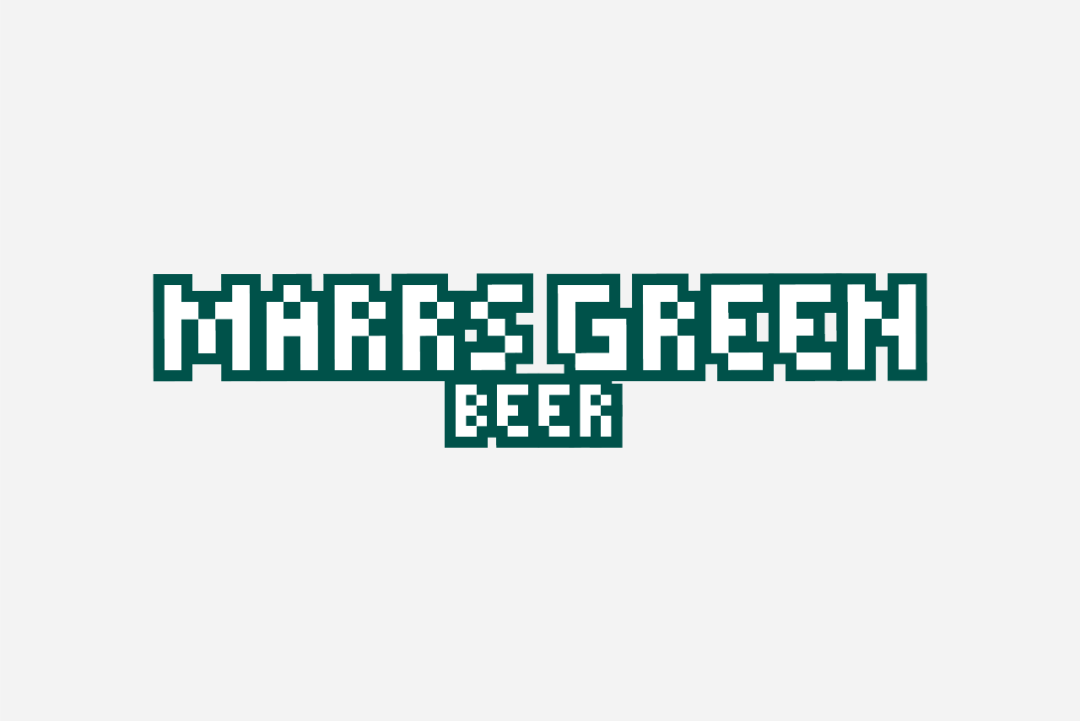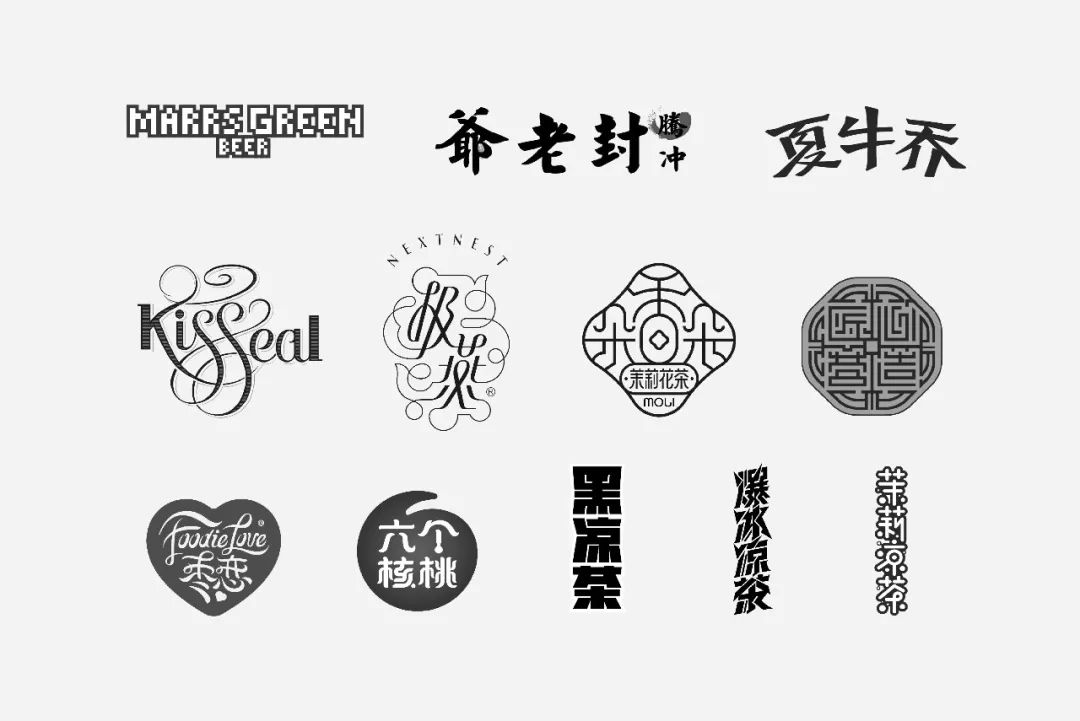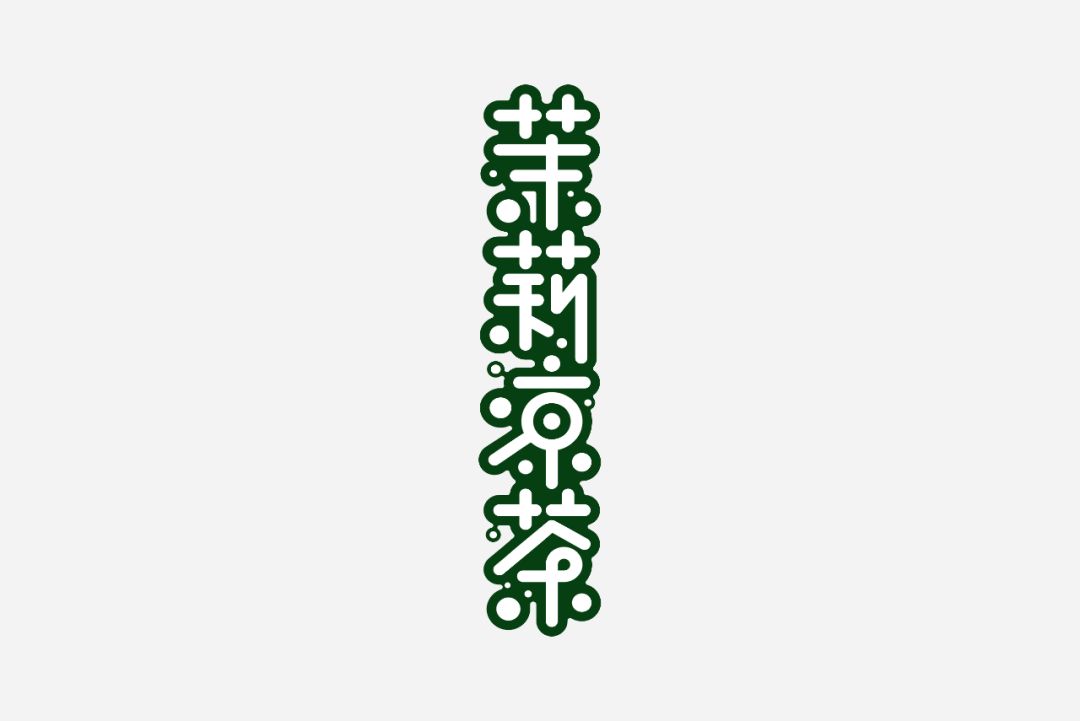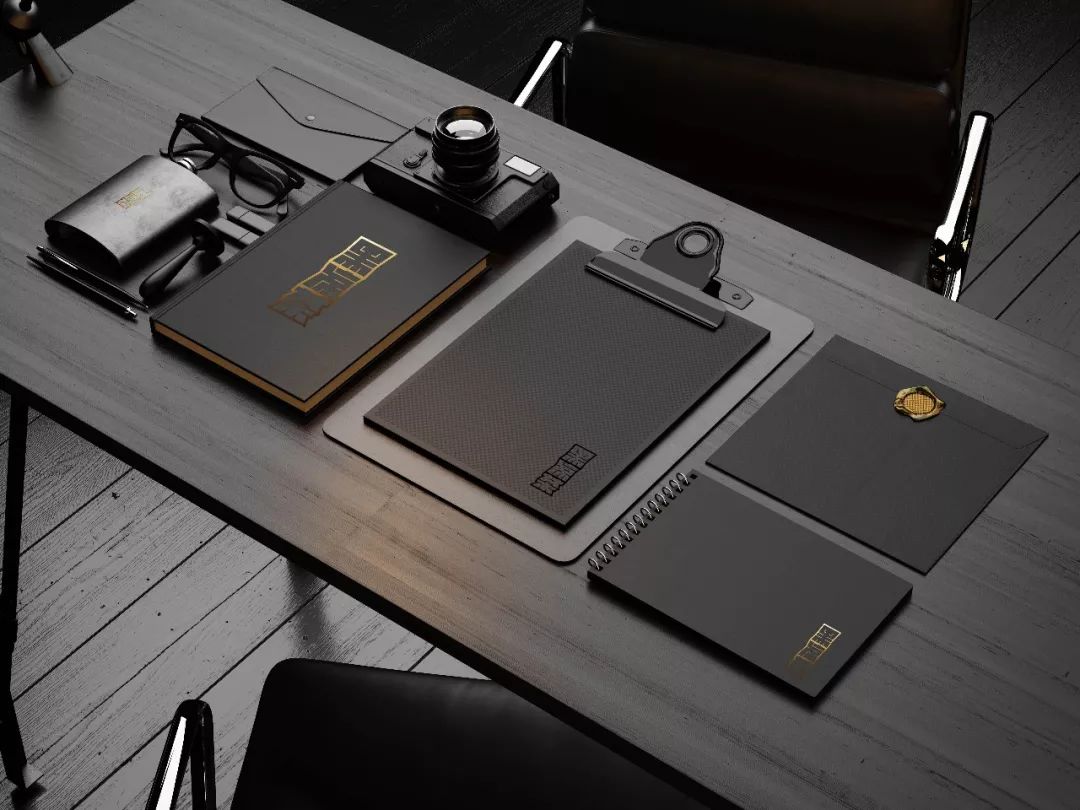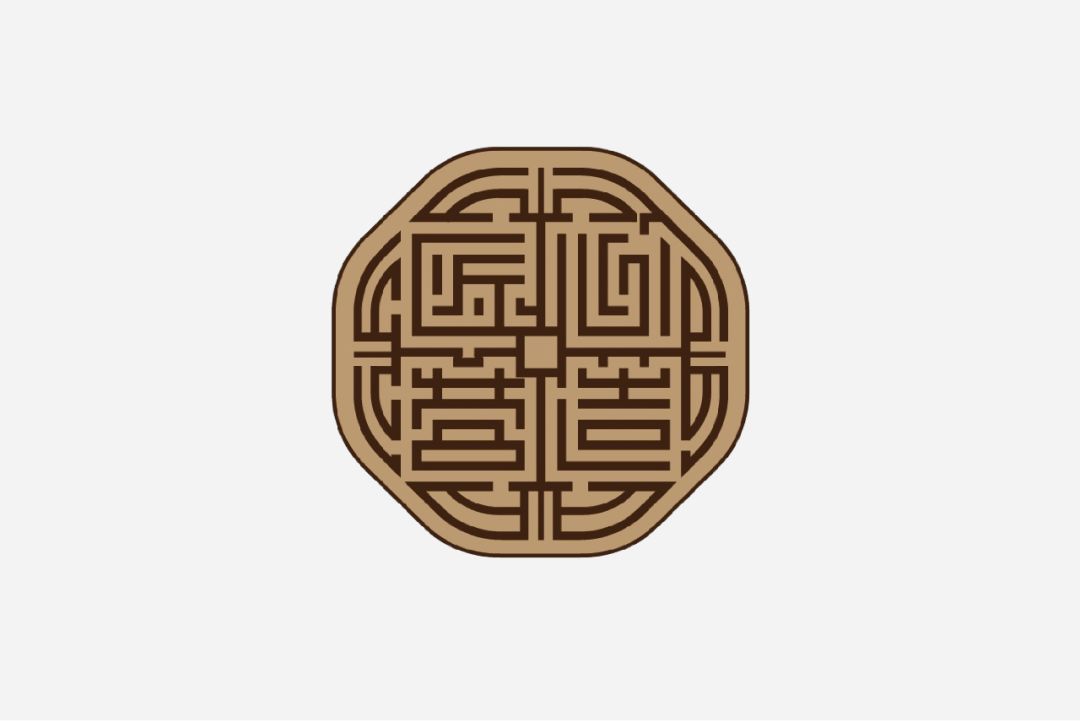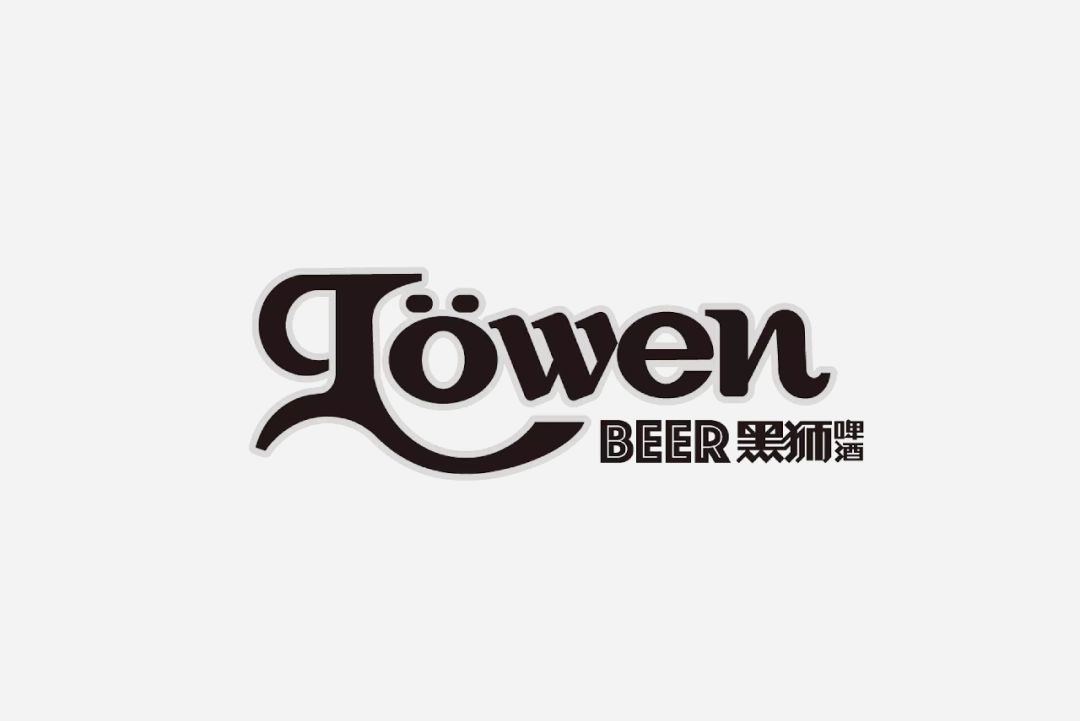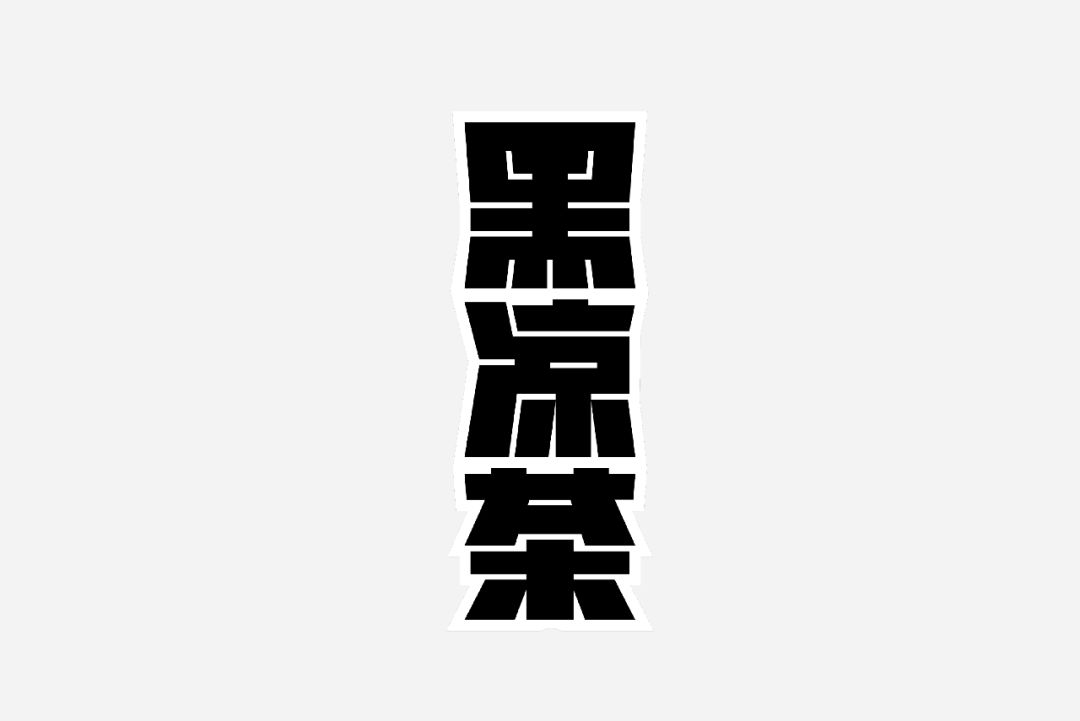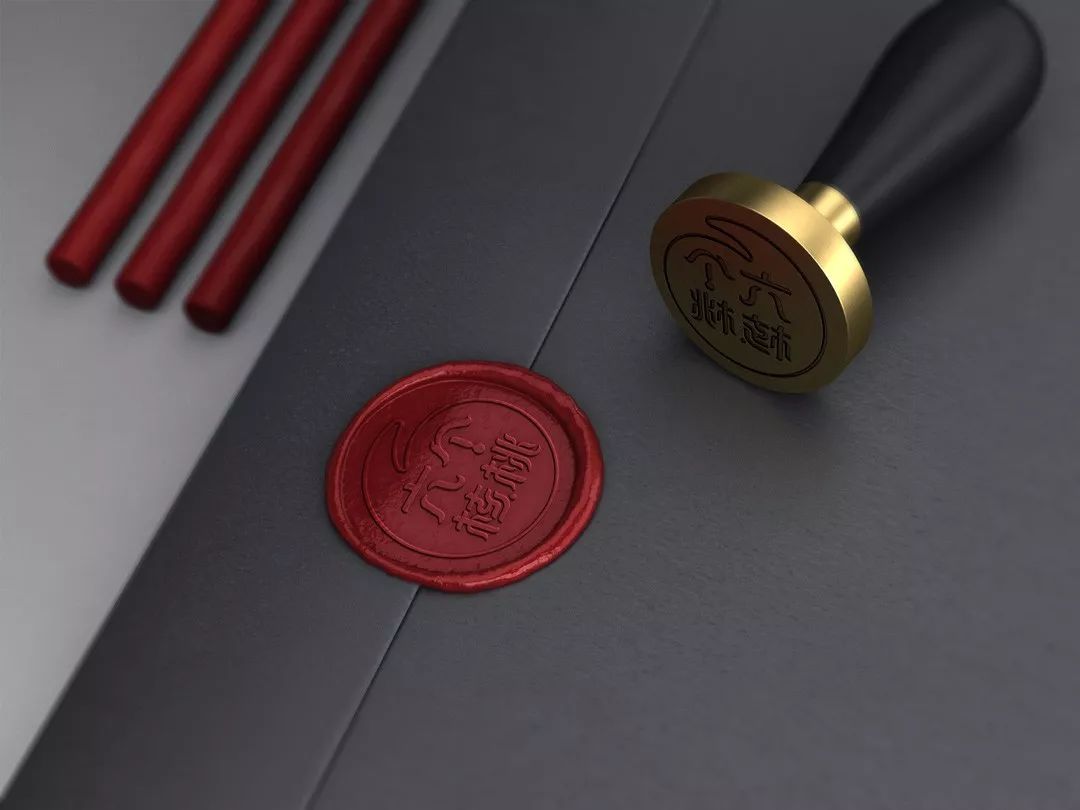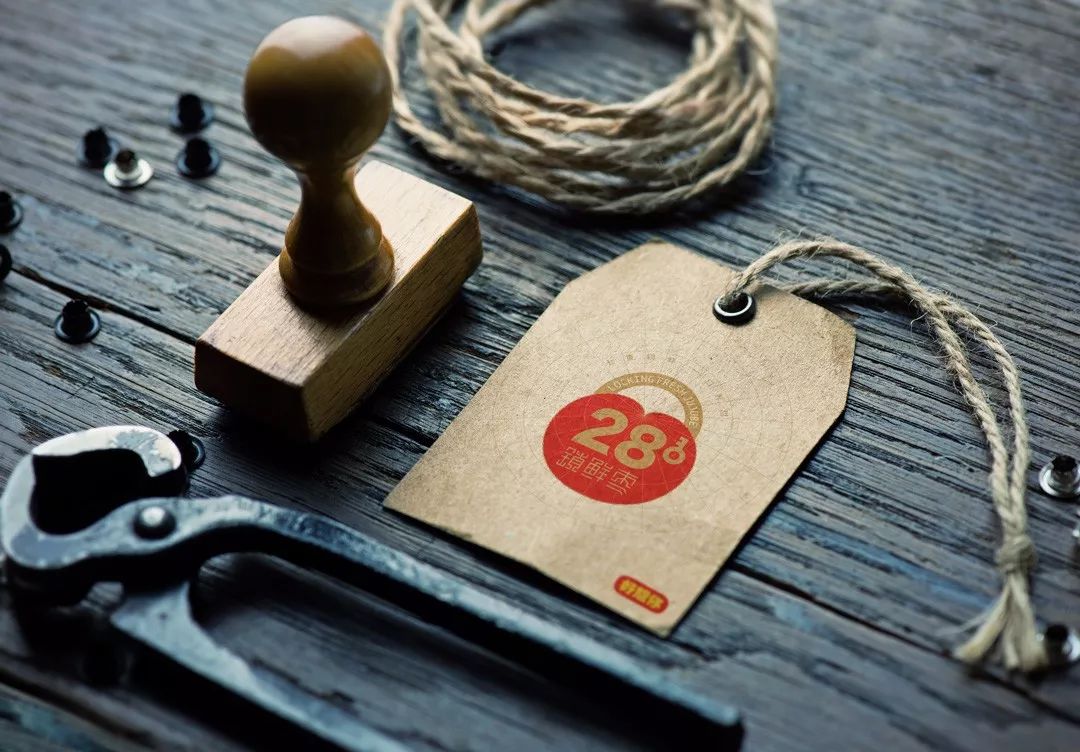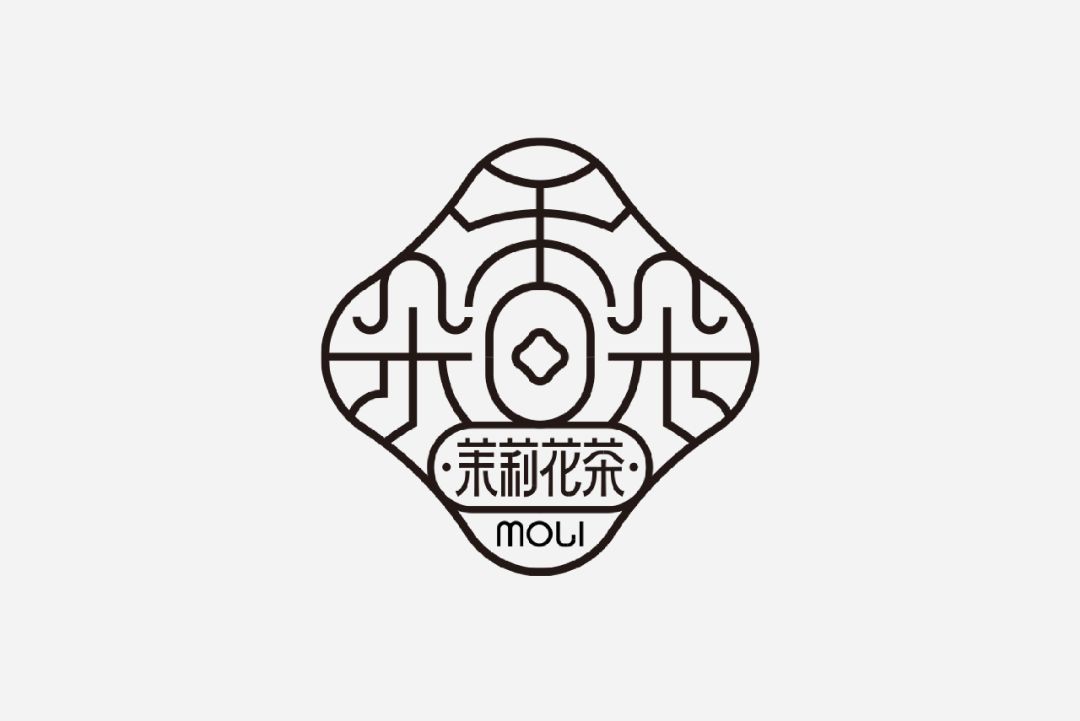
产品包装字体设计案例,那些品牌包装的字体“小心机”
在产品包装中
字体设计不仅将产品信息视觉化
同时也是品牌内涵的延伸
产品包装中的字体设计
与产品或者品牌的属性相关联
通过字体设计的形式美
可以加深品牌的视觉记忆点
本篇文章带大家一起来盘点一下,潘虎包装设计实验室出品包装中所涉及到的部分字体设计。
雪花·马尔斯绿
MARRS GREEN字体以俄罗斯方块为设计的灵感来源,并通过扁平化的几何图形将文字视觉化,并唤起消费者对童年电子游戏的情怀和情绪的感染力。
雪花·匠心营造
匠心营造将文字融入到古建筑窗棂之中,并以印章的形式,通过步步锦横平竖直的纹路在设计中沿袭中式的对称美。
雪花·黑狮
意大利体的变形,笔画粗黑,字体清晰,一般情况下用于报纸及杂质上的字体排版,该设计充分考虑其卖场主要是在夜场,可辅助瓶身图案增强产品的视觉识别。
王老吉·黑凉茶
王老吉黑凉茶是专为年轻人打造的一款重口味产品,字体以包装理念“王老吉被黑”引发我们对这款字体的趣味化打造,以简单粗暴的粗黑字体使黑凉茶的产品文化更加偏向年轻化,重金属感的色块强化了视觉认知。
王老吉·爆冰凉茶
在爆冰凉茶的设计中,我们希望结合口味创新致力视觉颠覆,打造一款专属于年轻人的王老吉。爆冰凉茶的字体从碎裂的冰块获取设计灵感,棱角分明的硬黑粗体笔划凸显文字的张力与碎裂感,与色彩明艳的波普风包装插画,产生强烈的视觉反差。
王老吉·茉莉凉茶
字体以简化手写体,给人清晰易辨认的视觉感,而且给人较柔和可爱的感觉,并且将茉莉花矢量化为扁平的几何圆点,容易让人联想到碳酸饮料中的气泡。
香朵朵·茉莉花茶
以窗棂勾勒的香朵朵字体,是结构与造型的和谐统一,“香朵朵”品牌名以对称化结构呈现,将字体符号化、视觉化,并使其艺术风格更加突出。
六 个 核 桃
以图形共用的方式对旧版的logo及字体做升级,保留了其主视觉色彩,对核心符号的塑造中强化了数字“6”,并将其扁平化呈现,是对品牌的趣味化呈现。字体从核桃乳的流动形态中提取,让人联想到产品的实体内容。虚实叠加,是六个核桃形与意的趣味化结合。
好想你·枣恋
采用手写体的斯宾塞字体,可口可乐的logo字体是其经典案例之一。以飘带的悠然跳跃之态,表现字体的连贯流畅和灵动飘逸之感,放大和重复优雅的米白色飘带,体现简约、活泼、大方的设计风格。
好想你·锁鲜枣
该字体在设计时运用了一些断笔和连笔,并通过几何化线条使字与字之间相互协调,简洁生动而不影响整体的识别。
极 燕
倩体的变形,字体本身具有优雅,柔美,华丽的特点,因此而得名倩体。同时又融入了英文手写体的装饰线(连笔部分)让字体更具有装饰性。
Kisseal寇思乐
衬线体与手写花体相结合,字体优美的曲线弧度与插画上代表爱情的经典故事完美结合,传达出浪漫感性的品牌情绪。
封 老 爷
该款字体结合产品的品牌故事,以软笔手写体打造怀旧感,包装的整体设计以新中国早期报刊排版为灵感来源来讲述云南乡绅封老爷的品牌故事,品牌名字体作为整版“报刊”的头条标题,以粗重的书法笔画带来强烈的视觉冲击。
夏 牛 乔
印刷体的变形,特点横细竖粗,多用于书刊,报纸,杂志等印刷品的标题,与包装插画和整体的配色相结合,打造出一种怀旧复古的感觉。